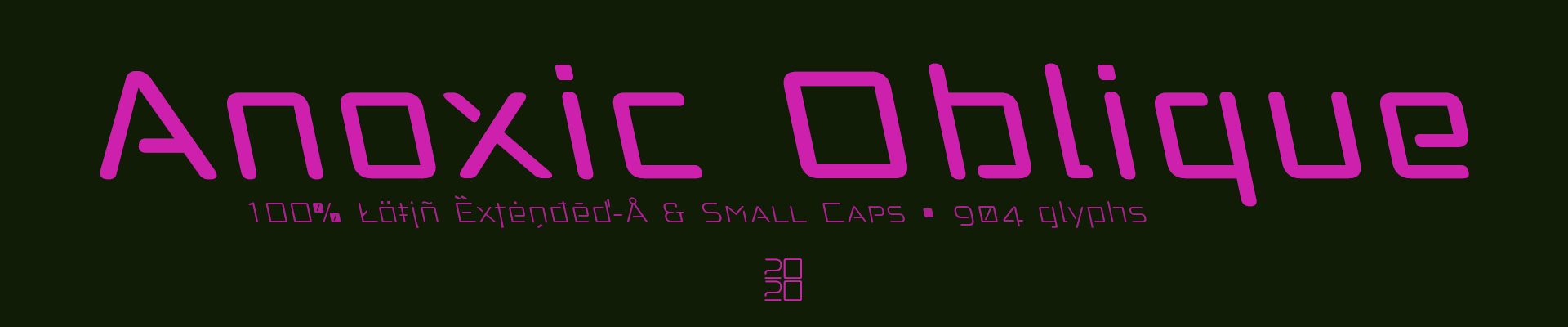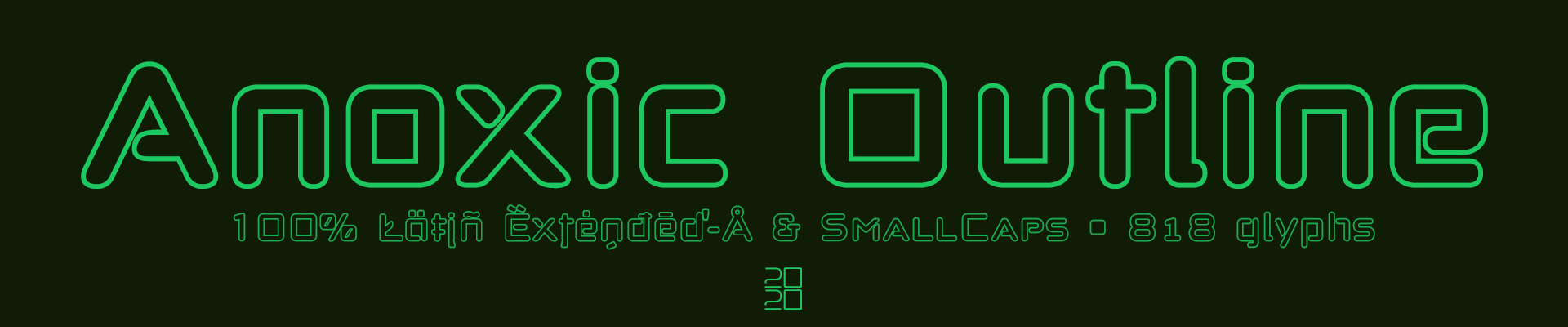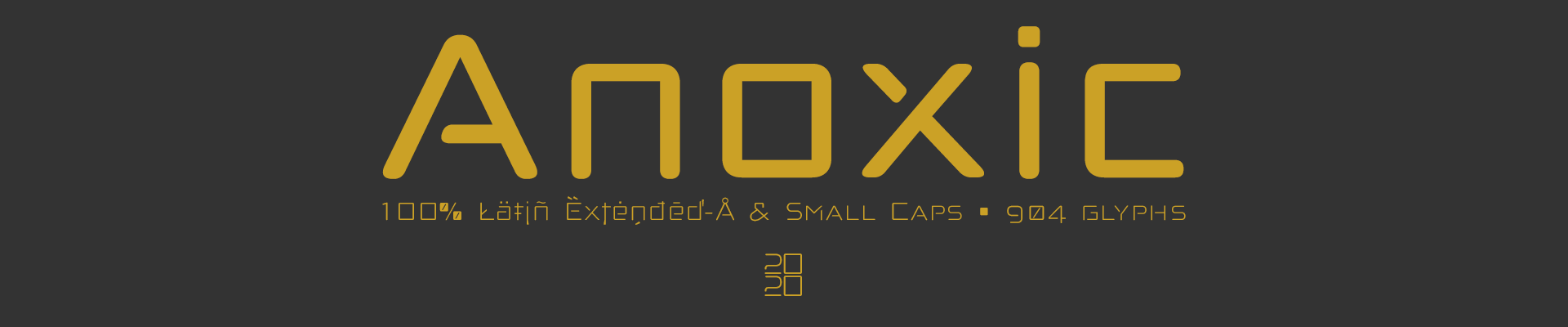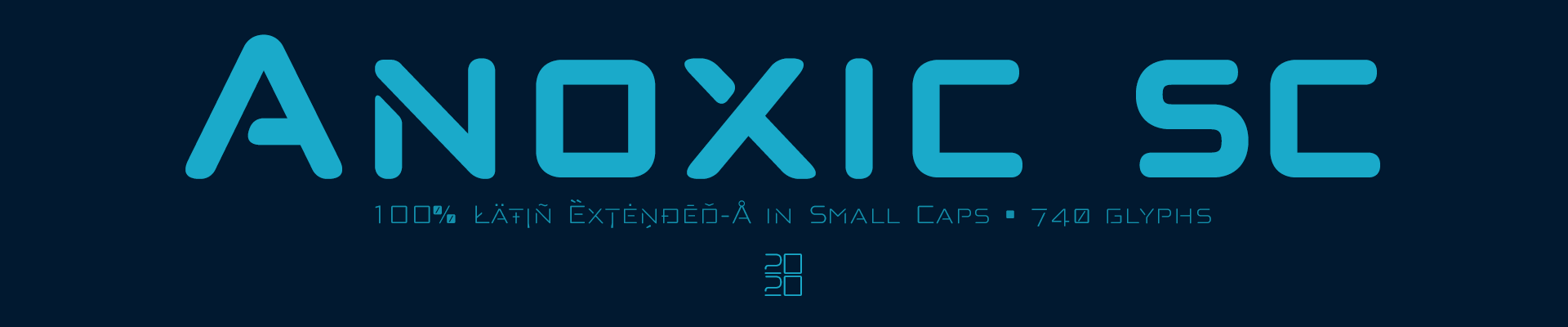
Estilo: Sans Serif, Semi-Stencil, Rounded, Small Caps, Outline, Oblique
Proporción: Light, Regular, Medium & Bold
Glyphs: 904
Alternates: 119
Latin-Extended: Latín Básico, Europa Occidental, Central & Oriental.
Funciones OpenType: Additional languages, All Alternates, Alternate Annotation Forms, Bitcoin, Capital Spacing, Contextual Alternates, Denominators, Discretionary Ligatures, Extended Fractions, Historical Forms, Inferiors, Kerning, Localized Forms, Numerators, Oldstyle Figures, Ordinals, Petite Caps, Scientific Inferiors, Slashed Zero, Small Capitals, Small Capitals From Capitals, Standard Ligatures, Stylistic Set, Subscript, Superior letters, Superiors, Superscript.
El aspecto tecnológico que da la proporción de los cortes, que la convierten en una fuente del tipo plantilla, han sido cuidadosos evitando los cortes superfluos. Su uso en diseño gráfico, editorial y publicidad garantiza originalidad, diferencia y máxima legibilidad, el kerning ha sido configurado cuidadosamente en todas las versiones. Unas fuentes muy versátiles para carteles publicitarios, vídeo juegos, títulos de cine, logotipos, publicaciones, etc. Incluyen el símbolo del Bitcoin y otras Cripto Monedas.
La fuente «Anoxic Roman & Oblique disponen en su versión comercial de un juego de 904 glifos (Latin Extended-A & Small Caps), la versión en versalita 704 glifos y 818 glifos para las versiones Outline, todas las versiones con soporte para cualquier idioma europeo o centro europeo. Anoxic también incluye funciones OpenType (Compatibles con InDesign, QuarkXpress, Photoshop e Illustrator.